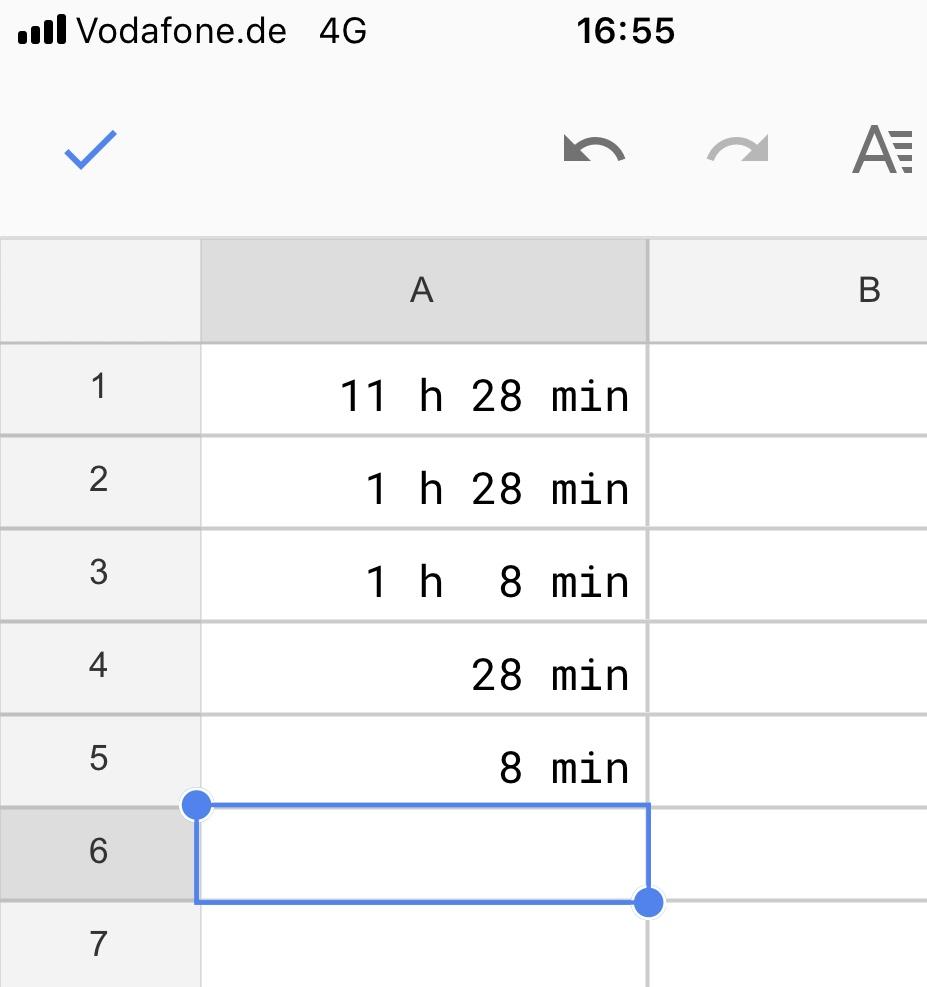
Datumsformat mit Wochentag: Buchstaben und Ziffern gleich breit, Punkt schmal
Es geht mir um einen Font für Datumsangaben wie
Mo 01.05.2017
Di 02.05.2017
in einer Tabellenkalkulation.
Dabei gefällt mir bei einer Proportionalschrift nicht, dass "Mo" und "Di" unterschiedlich breit laufen (auch wenn der Inhalt rechtsbündig ausgerichtet ist).
Wenn man jedoch einen Monospace-Font wählt, werden logischerweise auch die Punkte so breit wie alle anderen Zeichen.
Gibt es fertige Fonts, die für solche speziellen Zwecke geeignet sind, die also alle Buchstaben und Ziffern in gleicher Breite enthalten, den Punkt, das Komma und das Leerzeichen  jedoch in schmaler Breite?
Alle Anforderungen:
* Buchstaben und Ziffern dicktengleich
* Punkt, Komma und Leerzeichen schmaler als die Buchstaben und Ziffern
* Sans-Serif
* Versalziffern
* insgesamt schmal laufend
* keine zu dünne Schriftstärke (wie z.B. Courier New)
* keine "Füllobjekte" in der "0", wie ein Schrägstrich oder ein Punkt
* mindestens in den Schnitten Normal und Bold, gerne auch Italic
* gut auf dem Bildschirm lesbar, auch auf hochaufgelösten
Am Rande:
Was ist orthotypografisch bei der Datumsangabe eigentlich korrekt?
Muss noch ein Trennzeichen zwischen Wochentag und Datum?
Danke. In Axel sind die Buchstaben nicht gleich breit. Und die Null enthält einen Schrägstrich.
Ich würde da Tabstopps setzen, damit die Wochentage und Ziffern in einer Linie stehen. Korrekt wäre wohl ein Punkt, gefolgt von einem Komma hinter der Abkürzung des Wochentages. Das sieht aber nur grausig aus:
Mo., 01.05.2017
Di., 02.05.2017
Daher würde ich darauf pfeifen, weil jeder weiß, was mit Mo, Di, Mi gemeint ist. Die unterschiedliche Breite der Abkürzungen kann man durch Spationierung etwas ausgleichen, aber in meinen Augen sieht es schnell sehr erzwungen aus, wenn beispielsweise das i den Anschluss zum D verliert.
P.S.: Ich würde mich auch für eine bessere Lösung interessieren.
Für einen Font auf einer Website habe ich schonmal Glyphen aus einem Font entfernt. Das ging problemlos. Ich muss mich informieren, ob es grundsätzlich geht, Glyphen aus aus verschiedenen Fonts in einem neuen zusammenzufügen.
Ja, das sehe ich ebenso wie Du. ".," sehen fies aus.
Tabstops scheiden aus. Die Darstellung wird von der Tabellenkalkulation aus einem Zeitwert erzeugt. Die Darstellung beruht allein auf Formatangaben, nicht auf manuell eingegebenen Inhalten.
Am Rande:
Google Sheets erzeugt in der Regionaleinstellung "Deutschland" bei der Formatangabe "ddd" das Wochentagsformat "Di.", also mit Punkt. Der Punkt lässt sich leider nicht verhindern.
Wäre es eine Option, die Datumsangabe auf zwei Spalten zu Teilen: Eine Spalte für den Wochentag, eine andere für das Datum? Die eine kann ja über eine simple „= A1“-Formel den Inhalt der anderen kopieren. So mach ich das in meinen Tabellen, wenn ich Sachen bündig ausgerichtet haben will, ist im Prinzip die Tabellen-Kalkulations-Variante von Christians Vorschlag mit den Tab-Stops.
So ein Workaround ist denkbar, aber er ist doch reichlich umständlich und wartungsanfällig.
Denn der Zeitwert müsste dann per Formel in die Spalte für den Wochentag kopiert werden.
Auch bei Gestaltung durch Umrandungslinien/Innenabstände etc. müssten immer beide Spalten behandelt werden.
Davon unabhängig:
Nehmen wir mal an, so ein Remix eines Fonts ist ohne einen Riesenaufriß möglich:
Welche Monospace würdet ihr empfehlen?
Zurück zur Typografie:
Ich bin ziemlich sicher, die verkleinerte Darstellung der Nachkommastellen schonmal gesehen zu haben. AFAIR in technischen NASA-Dokumenten. Oder Daten in der Fliegerei. Es ging darum, die Größenordnung auch dann sicherer zu vermitteln, wenn das Auge wenig Zeit hatte.
Fällt euch dazu was ein?